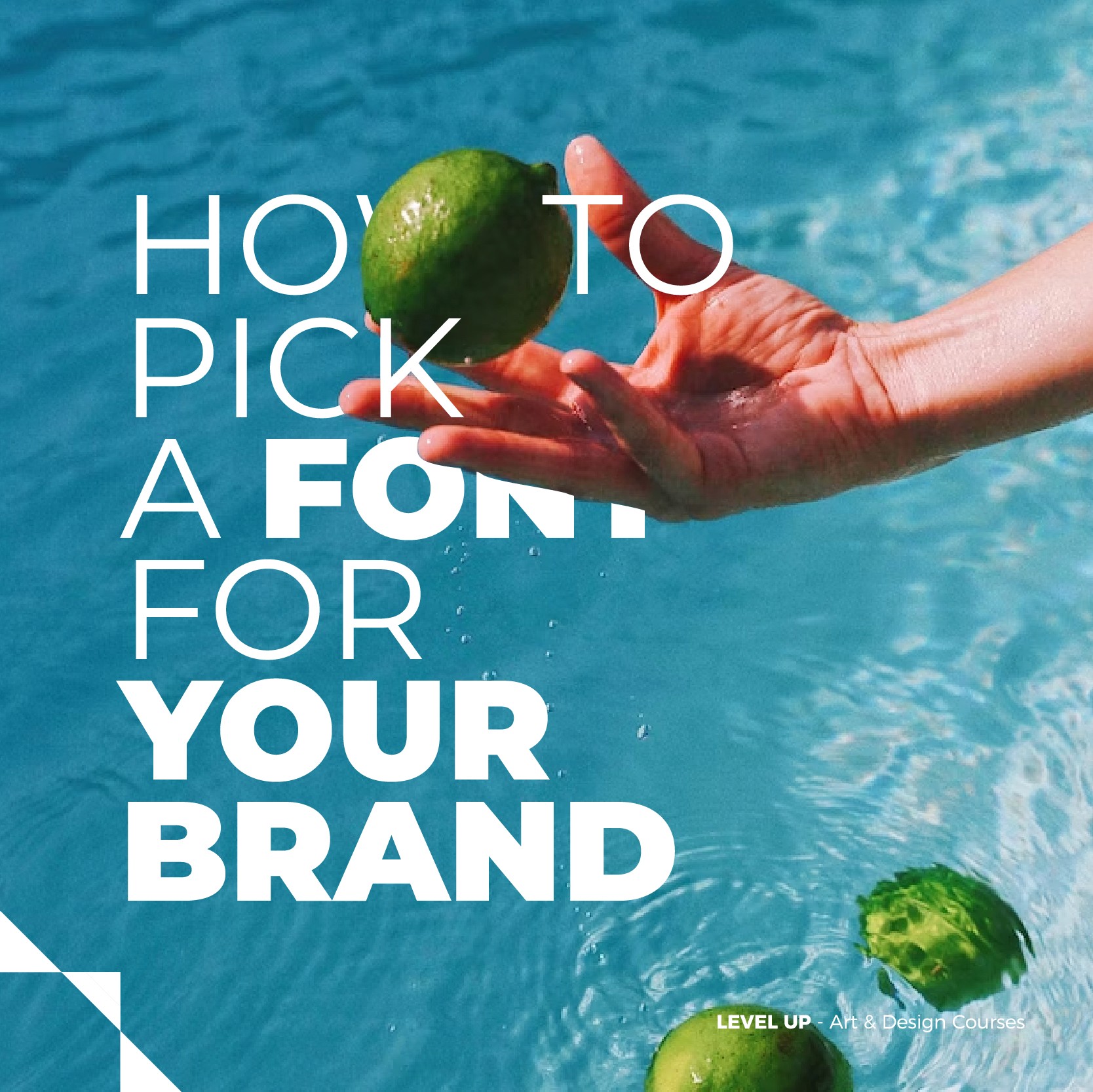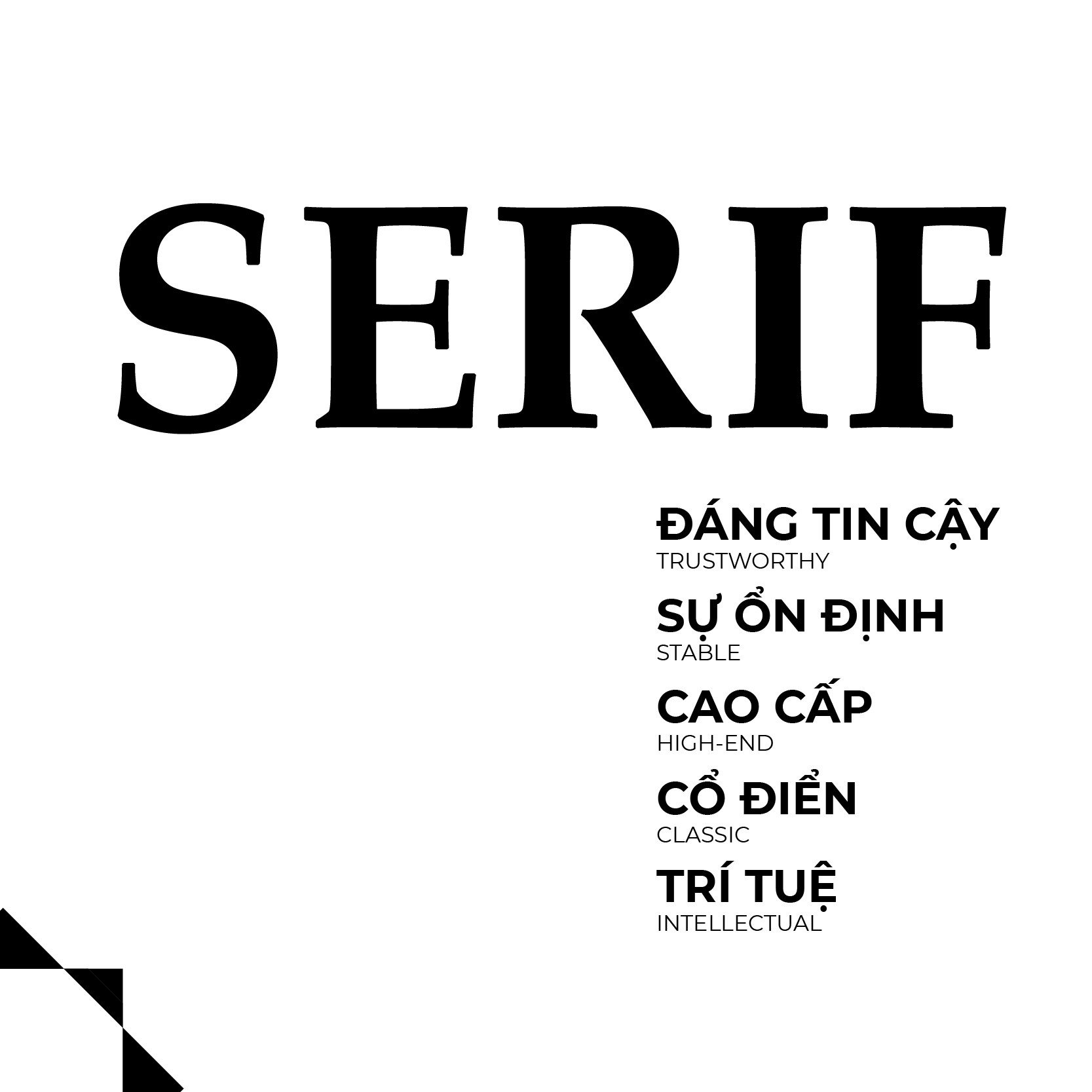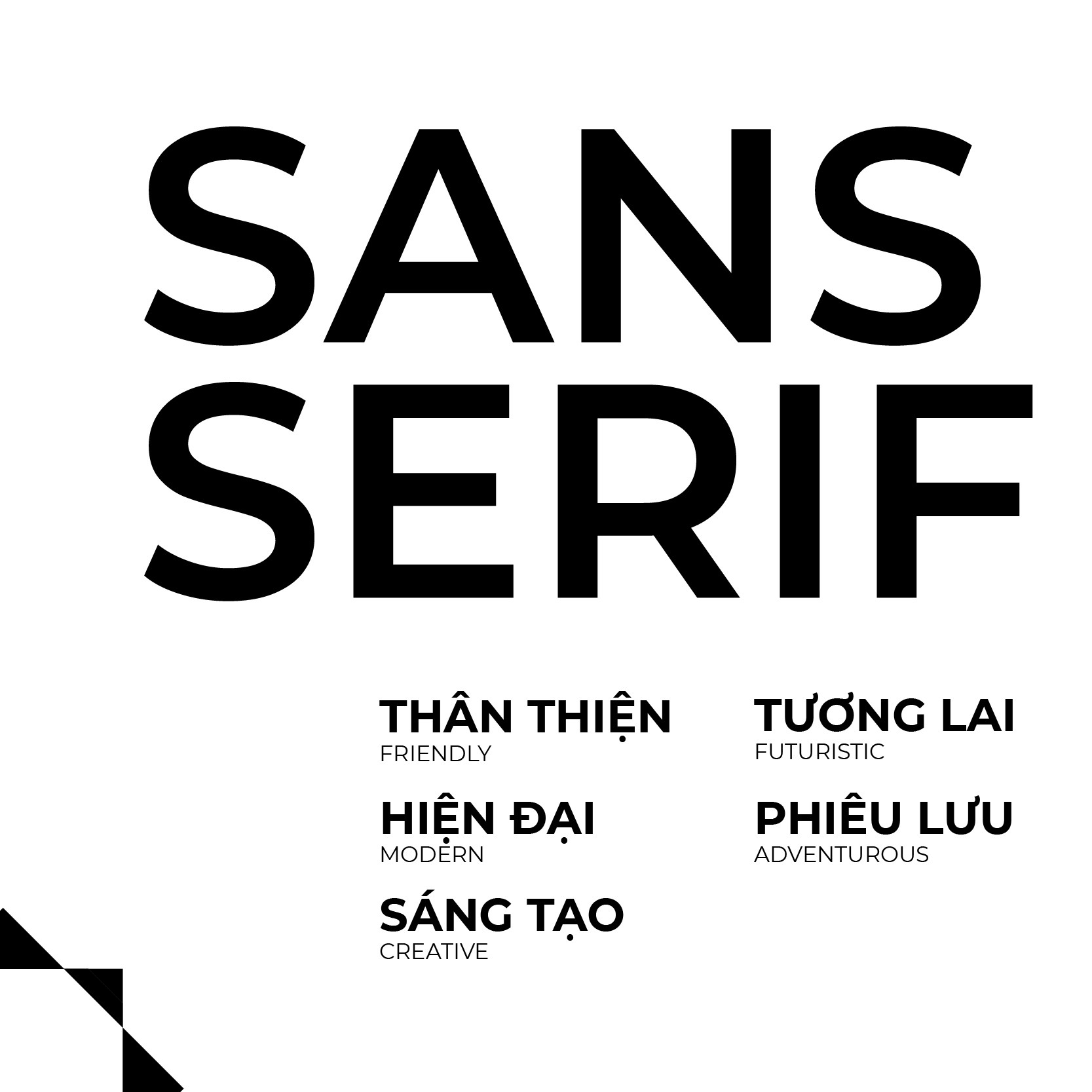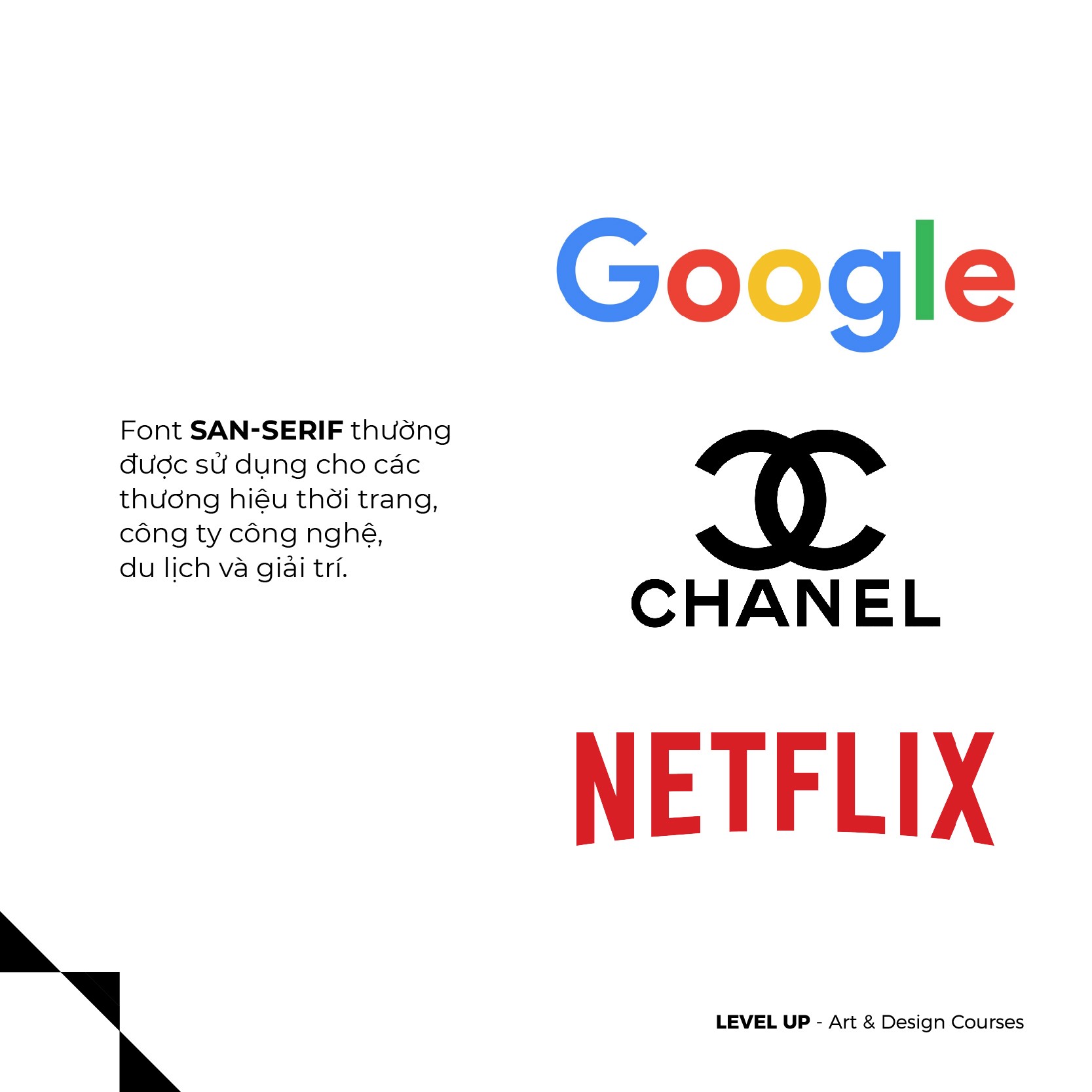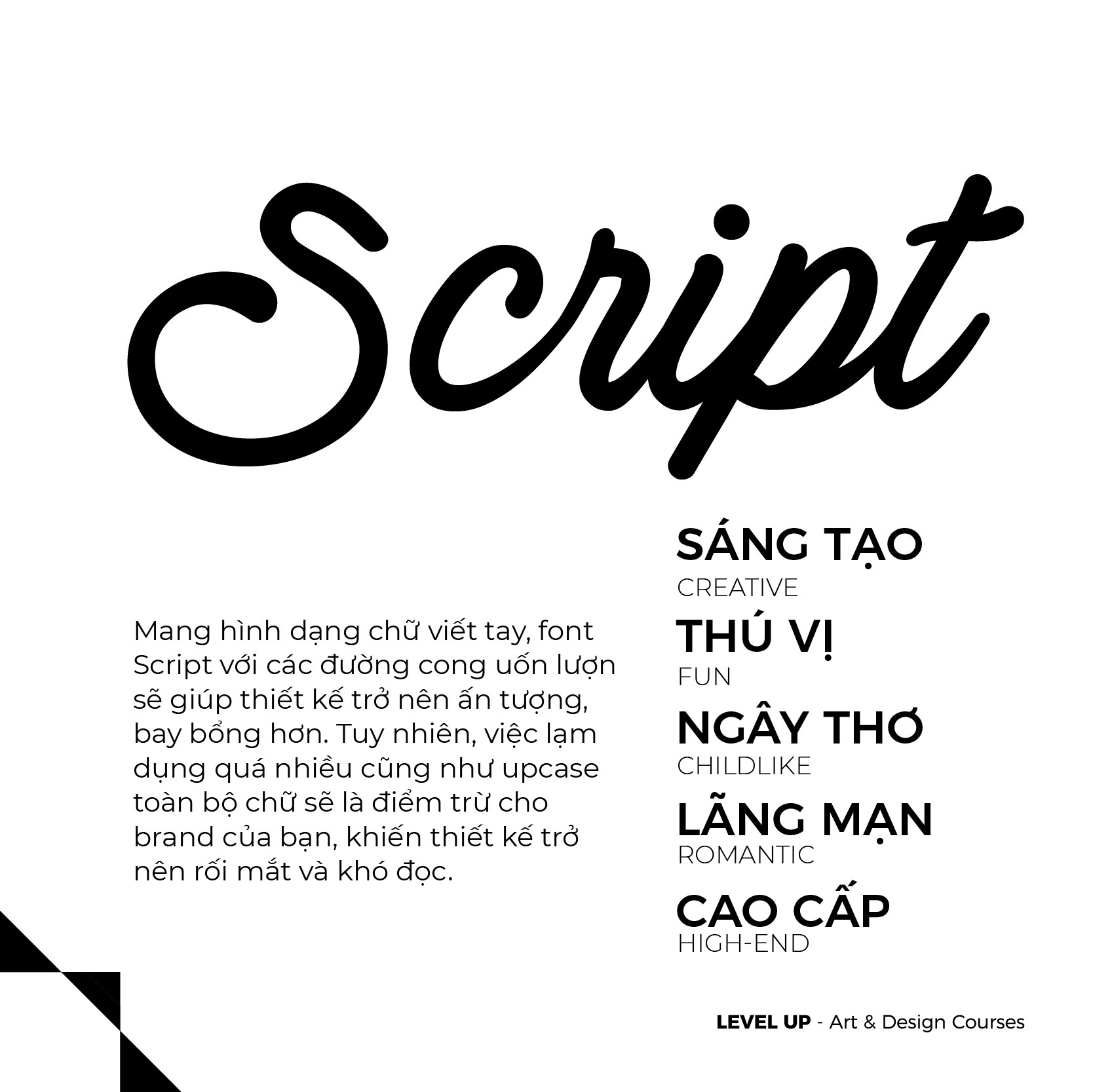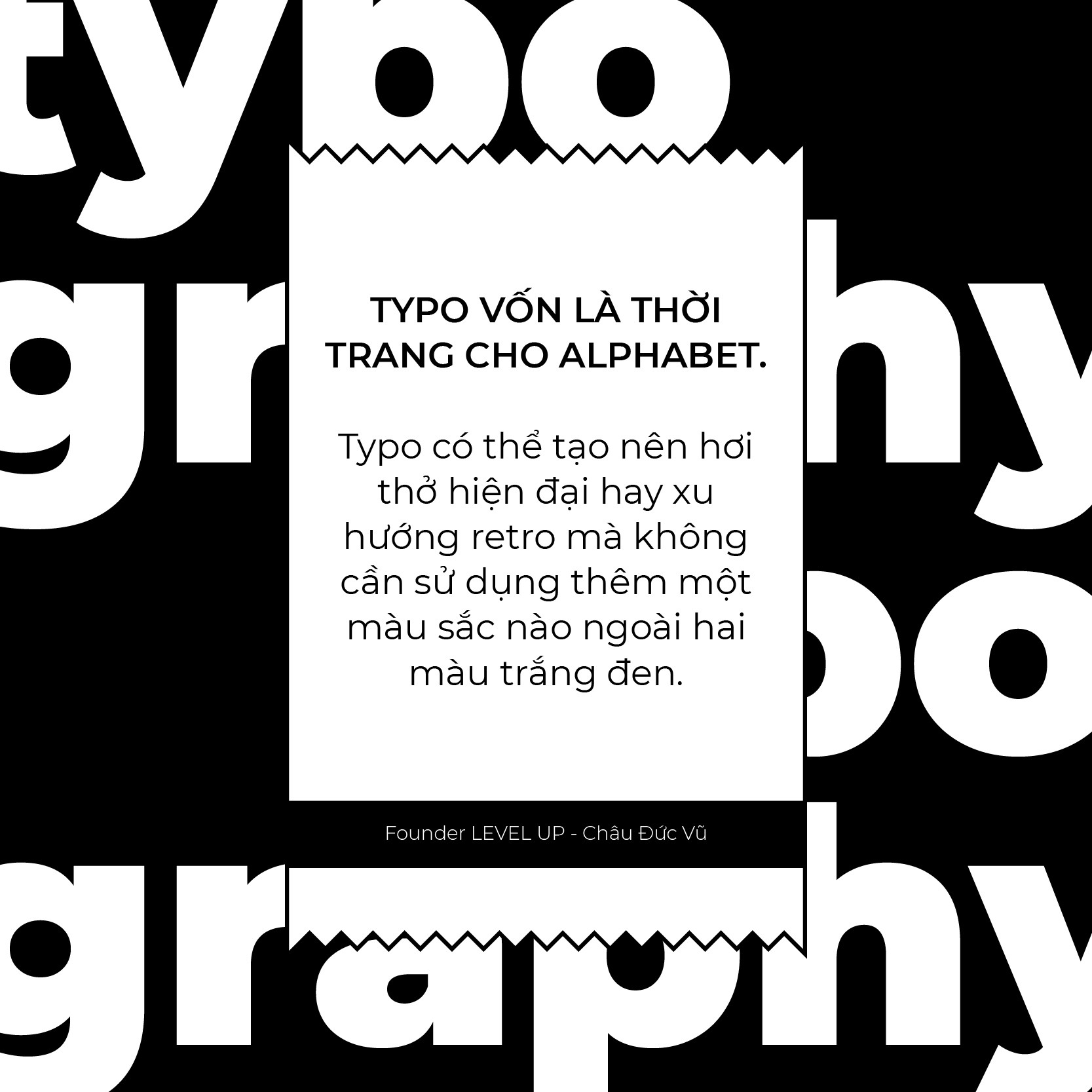
Chọn đúng font cho thương hiệu của bạn
Typography
Có thể bạn chưa biết, việc chọn ra font chữ tương thích và phù hợp là điều vô cùng quan trọng trong việc xây dựng thương hiệu. Bởi một font chữ chỉ đẹp thôi là chưa đủ mà ta cần nắm bắt được đâu là font chữ có khả năng tăng độ nhận diện và gắn với giá trị thương hiệu.
Quả thực, đó chẳng phải điều đơn giản. Làm thế nào ta có thể hiểu được phong cách và tinh thần của font chữ để nên một thương hiệu độc đáo? Hãy để LEVEL UP giúp bạn ngay với những kiến thức sau nhé!